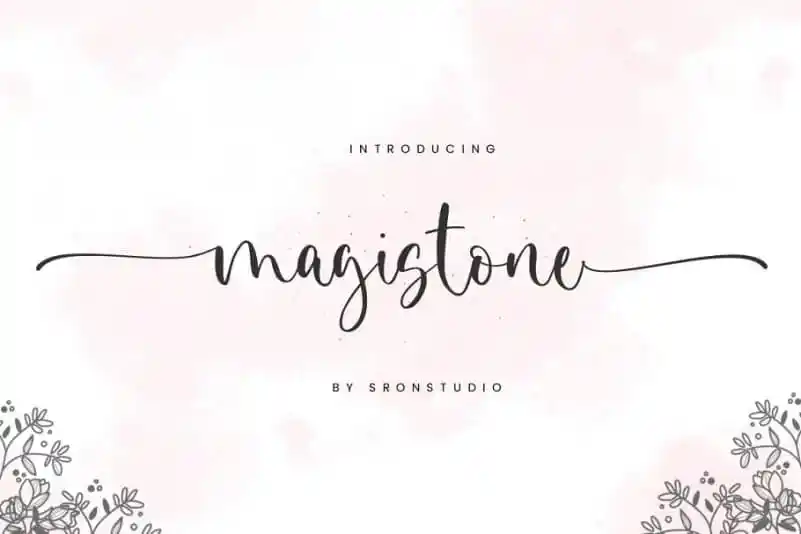
Magistone Calligraphy Font é uma elegante tipografia feita à mão seguindo o estilo moderno da calligrafia. Suave e sofisticada ao mesmo tempo, esta fonte é perfeita para diversas aplicações gráficas como design de produtos, embalagens, postais, convites e materiais promocionais. Ela foi criada por sartstudio na plataforma de designers 99designs e compartilhada com o mundo. Suas linhas fluidas e sutilezas elegantes tornam Magistone Calligraphy Font uma escolha ideal para quem busca um toque único em seus projetos. Perfeito tanto para criar design criativo, como para personalizar a identidade de marca ou embalagens de produtos, esta fonte oferece o brilho e sofisticação que você deseja sem comprometer sua autenticidade. Com seu formato moderno, Magistone Calligraphy Font se adapta perfeitamente a qualquer projeto em que você esteja trabalhando. Seja para adicionar uma personalização especial aos postais de aniversário ou enviar um convite criativo para eventos, ou simplesmente usar nas etiquetas de produtos e embalagens — esta fonte é definitivamente uma ótima escolha para qualquer aplicação visual. O charme desta fonte se torna ainda mais evidente quando usada em materiais promocionais, tais como posts no Facebook, anúncios ou até mesmo como um logotipo. A elegância e sofisticação da Magistone Calligraphy Font faz dela uma opção perfeita para aprimorar qualquer design. Seja você um designer de marca, criador de conteúdo digital ou simplesmente alguém que procura algo especial para seus projetos, Magistone Calligraphy Font tem tudo o que você precisa. Com sua capacidade única de transformar qualquer projeto em algo mais profissional e criativo, esta fonte é uma excelente adição ao seu coletivo de ferramentas gráficas.